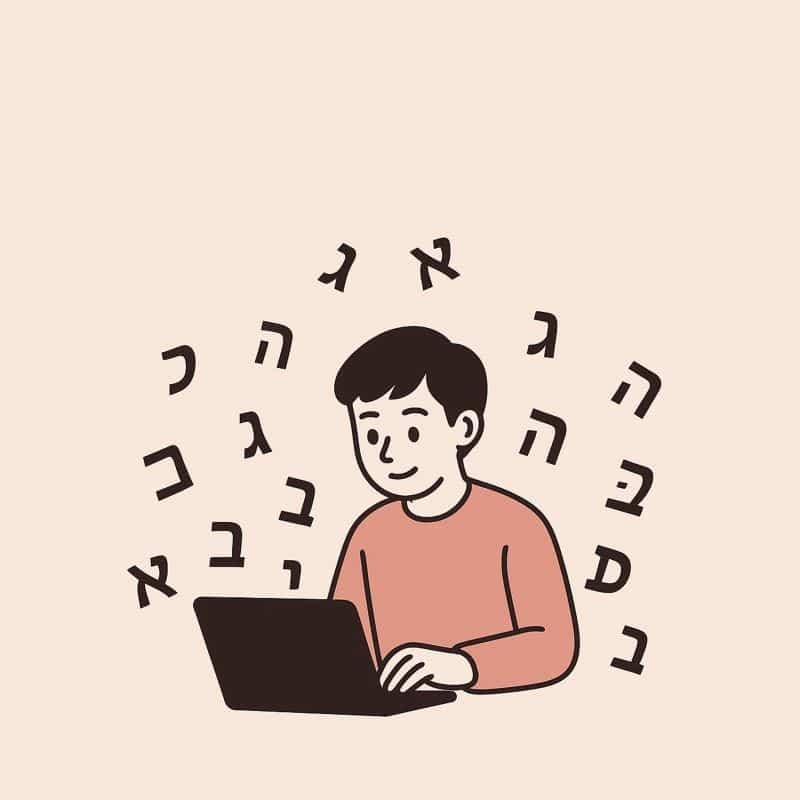
אחת מאבני היסוד של עיצוב גרפי היא הצורה של עיצוב האותיות, אך מעבר לאסתטיקה, זהו כלי רב-עוצמה שמגדיר מותגים, משפיע משמעותית על חוויית המשתמש ומעביר מסרים בצורה מדויקת.
בחירת הפונט הנכון יכולה לעשות את ההבדל בין עיצוב סטנדרטי לעיצוב בלתי נשכח. כאשר מדברים על טיפוגרפיה השראה, הכוונה היא לאופן שבו עיצוב האותיות משתלב ביצירתיות ובמסר הרחב יותר.
בעבר, עיצוב פונטים היה תחום מסורתי שהתבסס בעיקר על סגנונות ידניים ודפוס, אך כיום הוא מתפתח בקצב מהיר עם השפעות דיגיטליות, טכנולוגיות ואומנותיות.
המגוון הרחב של פונטים מיוחדים בעברית מאפשר למעצבים לחדש, לבלוט ולהתאים כל יצירה לשפה הוויזואלית שלה.
פונטים אינם רק ה“לבוש” של הטקסט, יש להם השפעה על הדרך שבה קהל היעד תופס את התוכן וסופג אותו.
בין אם מדובר במודעה פרסומית, בממשק משתמש של אפליקציה או בעיצוב לוגו לחברה – טיפוגרפיה השראה והבחירה בפונט הנכון הם קריטיים.
העתיד של פונטים בעיצוב טכנולוגי והתפקיד המהותי שהם משחקים בו, ברורים לנו היום יותר מאי פעם. הנה כמה דרכים לדוגמה שבהן עיצוב האותיות בחלק של הטקסט משפיע על העיצוב כולו:
אם תרצו להבין טוב יותר על עיצוב מקצועי עם פונטים בעברית ועל טיפוגרפיה השראה, הנה כמה כללי בסיס:
בעולם עיצוב הפרינט והדיגיטל, ניתן לראות שיטות שונות שבהן מעצבים משתמשים בפונטים כדי ליצור רושם ולספר סיפור:
העתיד של הכתב המעוצב הולך לכיוון טכנולוגי ומודרני יותר, עם מגמות כמו:
יש להתאים את הפונט לקהל היעד ולתחום העיסוק של בית העסק. לדוגמה, פונט יוקרתי יתאים למותגים יוקרתיים, כתב בסגנון בלון יתאים למותגים צעירים יותר, וכן הלאה.
כן, אפשרי בהחלט, אבל צריך לעשות זאת בזהירות. השילוב צריך להיות טבעי ולא כזה שיוצר עומס ויזואלי – למשל, שימוש בפונט אחד לכותרות לצד פונט אחר, קריא יותר ונעים יותר לעין, לטקסטים ארוכים.
הפונט וצורותיו יוצרים זהות מובהקת ונבדלת, מחזקים את המסר ומחדדים אותו, ומושכים את תשומת הלב של הלקוחות המדויקים לעסק.
לסיכום, טיפוגרפיה השראה היא הרבה יותר מהנחת טקסט – היא שפה עיצובית בפני עצמה. פונטים יכולים להפוך כל עיצוב לשובה עין, להעביר מסר חד וליצור חוויית משתמש טובה יותר. בואו לגלות איך פונטים יכולים להגדיר מחדש את הדרך שבה הקהל רואה את המותג שלכם עם ליה פונטים.